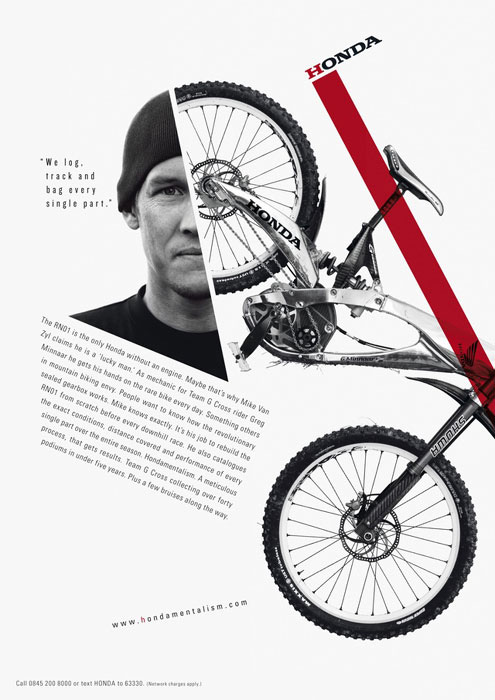
Sans avoir eu à me fendre moi même d’une créa pour vous montrer d’autres possibles dans l’univers visuel du vélo, voici une maquette vu sur le site de Cosas visuales qui montre d’autres pistes pour exprimer la novation et la modernité du vélo de ville. Bien sûr la référence aux années 20 de la Russie de Lenine et Staline sont évidentes, mais d’autres graphistes de renom s’en sont également inspiré pour signifier des tendances sociales modernes. Il suffit d’examiner la majeure partie de l’œuvre de Neville Brody (en tous cas, la période qui l’a rendu célèbre) pour voir que cette tendance DaDa et constructiviste peut exprimer bien plus que les idéologies de masse d’une époque fascisante. Construire plutôt que de subir, intégrer un outil-ludique-objet dans son univers de tous les jours pour transformer sa vie quotidienne, s’approprier les deux roues motrices d’un déplacement individuel pour aller à la rencontre de l’autre… voici des thèmes que le graphiste contemporain peut explorer autrement que par la création maladroite d’un logo velib’ (sans accent) digne de la maternelle.
Au fond si j’avais été consulté pour assurer cette communication, j’aurais sans doute été plus proche des codes visuels de Nike ou Adidas qui ont expérimenté depuis longtemps ce segment marketing et compris l’intérêt d’associer humanisme Rabelaisien à modernité techno-sociale… «un esprit sain dans un corps sain»